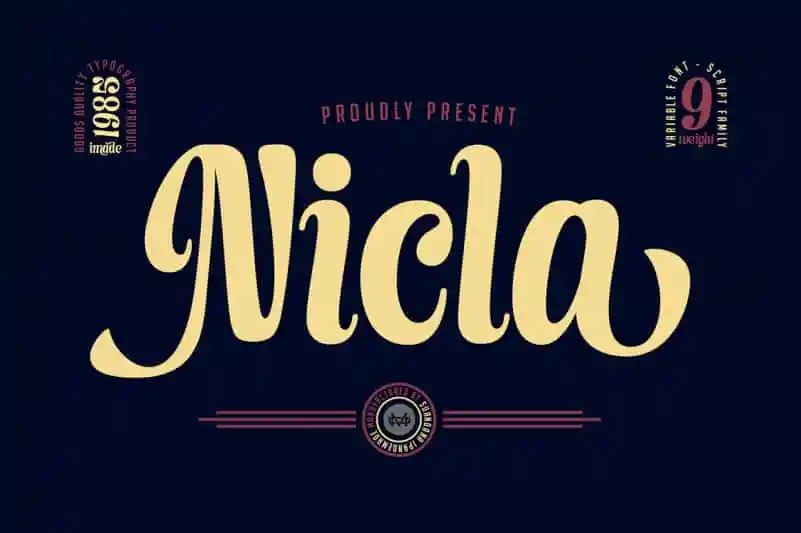
A fonte ‘Nicla Script Font’ é uma famosa família de letras cursivas, cheia de detalhes refinados e ligaturas perfeitas que adicionam charme ao seu trabalho. Ela foi criada pelo designer madeDuk, com um design cuidadosamente elaborado para fornecer suporte a várias línguas, além do inglês tradicional. Sua aparência elegante e única traz uma resolução notável às suas criações digitais. Com alternativas de letra únicas em abundância, Nicla Script oferece o prazer de trabalhar com um conjunto diversificado de opções para tornar cada projeto mais especial. Seja você criando cartazes de evento, desenvolvendo design gráfico ou apenas adicionando um toque a seu próximo documento pessoal, este é um recurso fonte incrivelmente útil que complementa qualquer projeto.